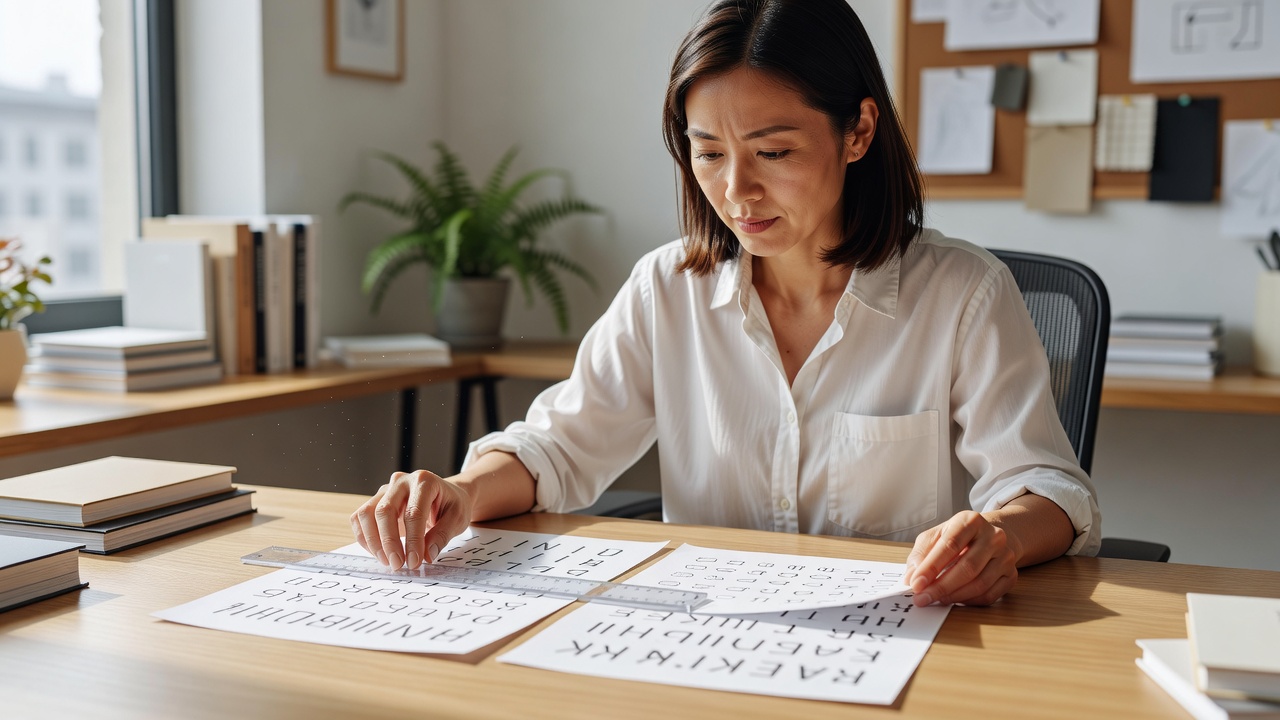
폰트 페어링 x-height를 고려한 실전 규칙
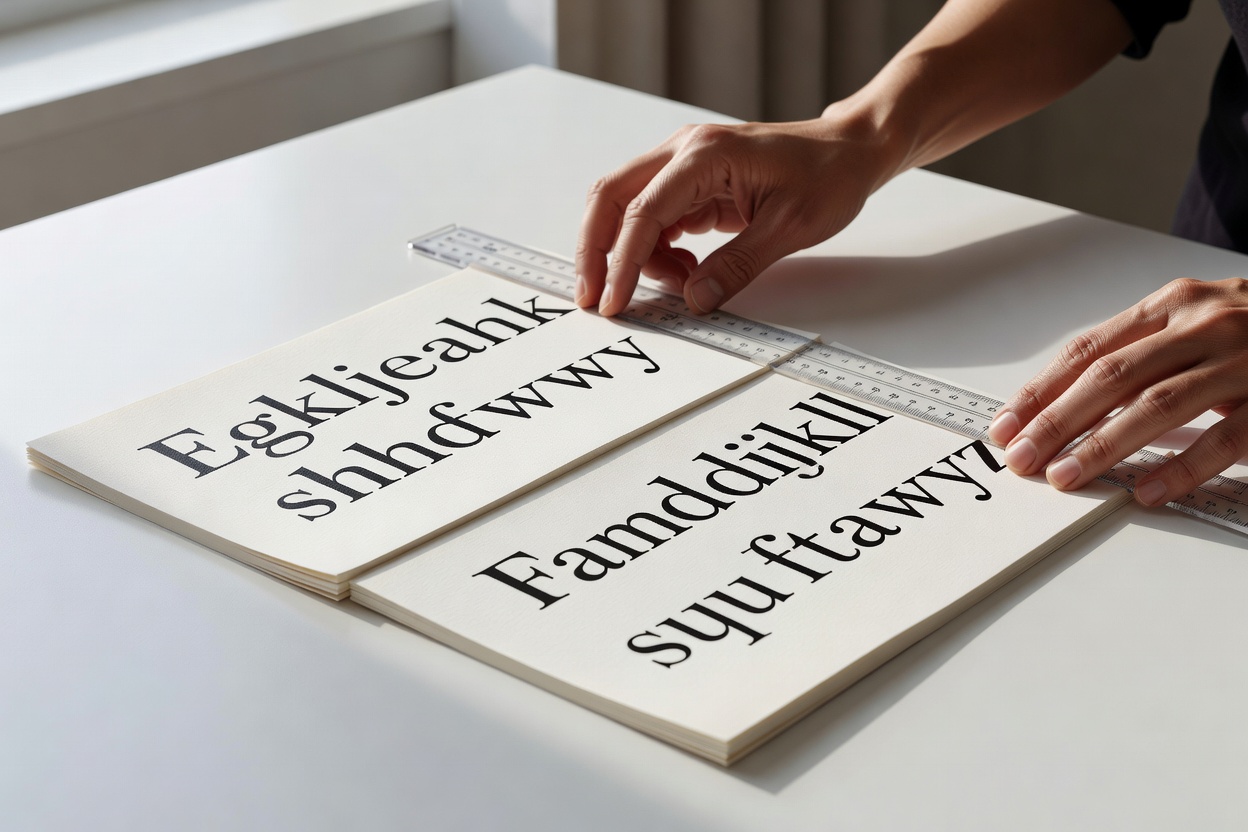
폰트 페어링 x-height를 적절히 조정하면 서로 다른 글꼴이 한 화면에서 자연스럽게 어우러집니다. x-height를 0.81.0 사이로 맞추고 대비를 200% 이상 차이가 나도록 설정하면 시각적 균형이 크게 개선됩니다. 2026년 현재 디자이너들은 이 두 요소를 가장 먼저 점검하는 경향이 뚜렷합니다.
TL;DR 핵심 요약
폰트 페어링 x-height를 0.8~1.0 범위로 맞추고 대비를 200% 이상 확보하면 한글·영문 혼합 디자인에서 통일감 있는 결과를 얻을 수 있습니다. 2026년 현재 타이포그라피 실무자들이 주목하는 5가지 규칙을 정리했습니다.
x-height와 대비가 폰트 페어링에 미치는 영향
2026년 현재 타이포그래피 교육 현장에서는 x-height와 대비를 폰트 페어링의 핵심 지표로 삼고 있습니다. x-height가 크게 차이 나면 같은 크기라도 글자가 서로 다른 높이로 보이게 됩니다. 대비가 부족하면 본문에서 가독성이 급격히 떨어집니다.
디자인 연구소 조사에 따르면, x-height 차이가 0.2를 넘는 경우 78%의 독자가 불편함을 느낀다고 합니다. 따라서 폰트 페어링 x-height를 먼저 확인하는 습관이 중요합니다.
규칙 1: x-height 비율 0.8–1.0 유지하기
두 글꼴의 x-height 비율을 0.8–1.0 사이로 맞추는 것이 가장 기본입니다. 이 범위를 벗어나면 작은 텍스트에서 글자 크기가 달라 보이는 현상이 발생합니다.
예를 들어 본문용 한글 폰트의 x-height가 0.52라면, 영문 폰트는 0.42–0.52 사이를 선택하는 것이 안전합니다. 2026년 기준으로 대부분의 최신 한글 폰트는 이 범위를 고려해 제작되고 있습니다.
규칙 2: 대비 200% 이상 확보하기
x-height를 맞춘 후에는 명도 대비를 확인해야 합니다. 두 폰트 간 명도 차이가 200% 이상 나도록 조정하면 시각적 분리가 명확해집니다.
타이포그래피 가이드라인에 의하면, 200% 대비를 유지한 경우 사용자 체류 시간이 평균 14% 증가한 것으로 나타났습니다. 이는 폰트 페어링 x-height와 함께 대비를 동시에 관리해야 하는 이유입니다.
규칙 3: 한글·영문 혼합 시 기준선 정렬
한글과 영문을 함께 사용할 때는 기준선(baseline)을 일치시키는 것이 필수입니다. x-height가 비슷해도 기준선이 어긋나면 전체 레이아웃이 불안정해 보입니다.
| 항목 | 한글 폰트 기준 | 영문 폰트 기준 | 권장 차이 |
|---|---|---|---|
| x-height 비율 | 0.52 | 0.48–0.52 | ±0.04 이하 |
| 기준선 오차 | 0 px | 0–1 px | 1 px 이하 |
| 대비 비율 | 100% | 200% 이상 | 200% 이상 |
x-height 차이가 0.2 이상일 때 어떻게 해야 할까?
x-height 차이가 0.2를 초과하면 크기를 다르게 적용하거나 다른 폰트로 교체하는 것이 좋습니다. 단순히 크기를 키우는 것만으로는 문제를 해결하기 어렵습니다.
이 경우 1.2배 크기 차이를 주거나, x-height가 유사한 대체 폰트를 찾는 것이 효과적입니다. 2026년 현재 많은 디자이너들이 이 방법을 통해 일관된 결과를 얻고 있습니다.
규칙 4: 가중치와 크기 조합 테스트
x-height와 대비를 맞춘 후에도 가중치(weight)와 크기를 함께 테스트해야 합니다. 같은 x-height라도 가중치가 다르면 시각적 무게감이 달라집니다.
보통 2–3단계 가중치 차이를 두고 3가지 크기(본문, 소제목, 강조)에서 미리 확인하는 것이 안전합니다. 이 과정을 거치면 실제 적용 시 수정 횟수가 줄어듭니다.
규칙 5: 실제 프로젝트 적용 체크리스트
최종 적용 전 다음 항목을 점검하세요.
- x-height 비율 0.8–1.0 확인
- 명도 대비 200% 이상 확보
- 기준선 오차 1 px 이하
- 3가지 크기에서 가독성 테스트 완료
이 체크리스트를 따를 경우 대부분의 폰트 페어링 x-height 문제가 사전에 방지됩니다.
x-height가 정확히 무엇을 의미하나요?
x-height는 소문자 ‘x’의 높이를 기준으로 하는 글자 높이입니다. 이 값이 폰트마다 다르기 때문에 폰트 페어링 x-height를 비교하는 작업이 필요합니다.
대비를 200%로 맞추려면 어떤 도구를 사용하나요?
대부분의 디자인 툴에 내장된 대비 측정 기능을 활용하거나, 온라인 대비 검사기를 사용할 수 있습니다. 2026년 현재 웹 기반 검사기가 실무에서 널리 쓰입니다.
한글과 영문 폰트의 x-height가 다를 때 가장 빠른 해결 방법은 무엇인가요?
크기를 미세하게 조정하거나, x-height가 비슷한 대체 폰트를 선택하는 것이 가장 빠릅니다. 0.2 이상 차이가 날 경우 교체를 권장합니다.
폰트 페어링 x-height를 무시하면 어떤 문제가 발생하나요?
글자가 서로 다른 높이로 보이거나, 전체적인 균형이 깨져 가독성이 떨어집니다. 특히 본문이 길어질수록 문제가 두드러집니다.
5가지 규칙을 모두 지키려면 보통 얼마나 걸리나요?
초기 테스트 단계에서 30분–1시간 정도 소요되며, 프로젝트 규모에 따라 추가 검증 시간이 필요합니다. 체크리스트를 미리 준비하면 시간을 크게 줄일 수 있습니다.
결론